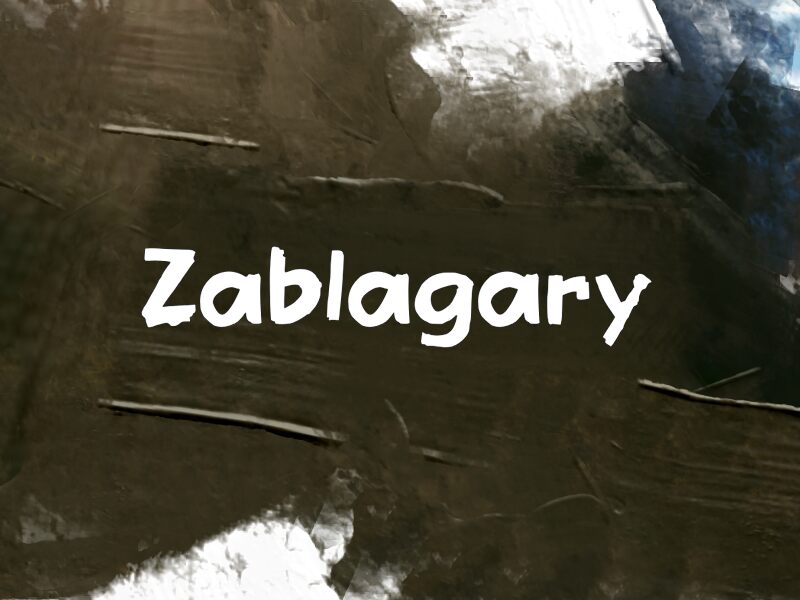
Zablagary od Wep je bezplatné písmo typu brush, které definují výrazné tahy štětcem a rozbité hrany, díky čemuž písmena působí, jako by byla právě teď čerstvě namalovaná. Tvary zůstávají široké a vzpřímené, ale otřepané konce a mírně nepravidelný rytmus zabraňují tomu, aby působilo příliš uhlazeně nebo strojeně.
Tato textura dodává krátkým nadpisům, plakátům, obalům alb nebo grafice na sociální sítě přímý, ručně malovaný nádech bez nutnosti dalších efektů. Skvěle se hodí pro branding kaváren nebo pozvánky na akce, kde povrch suchého štětce zajistí vizuální zajímavost a udrží pár slov v pohybu.
Zablagary
Prezentace a vizuální ukázka písma Zablagary